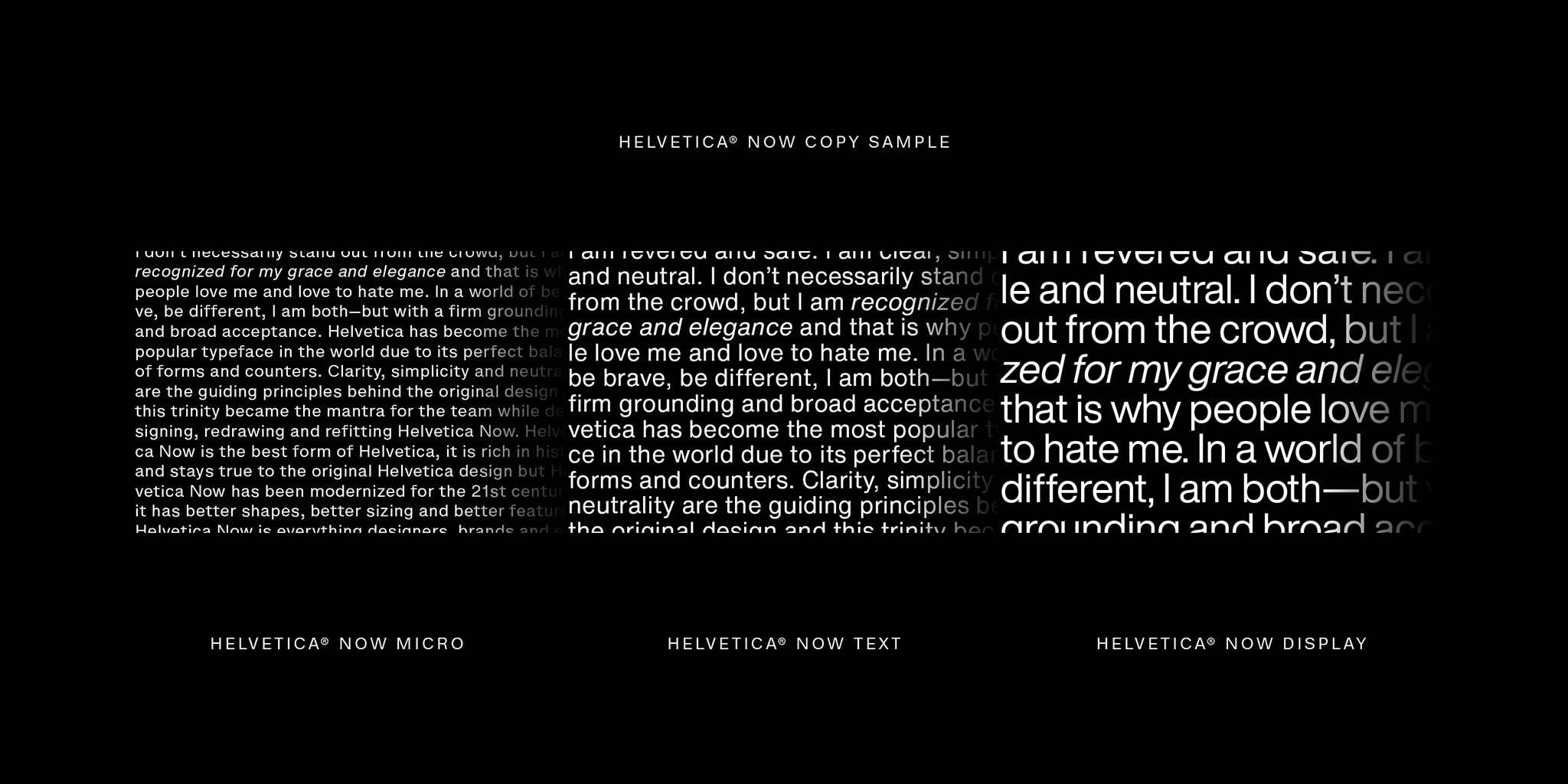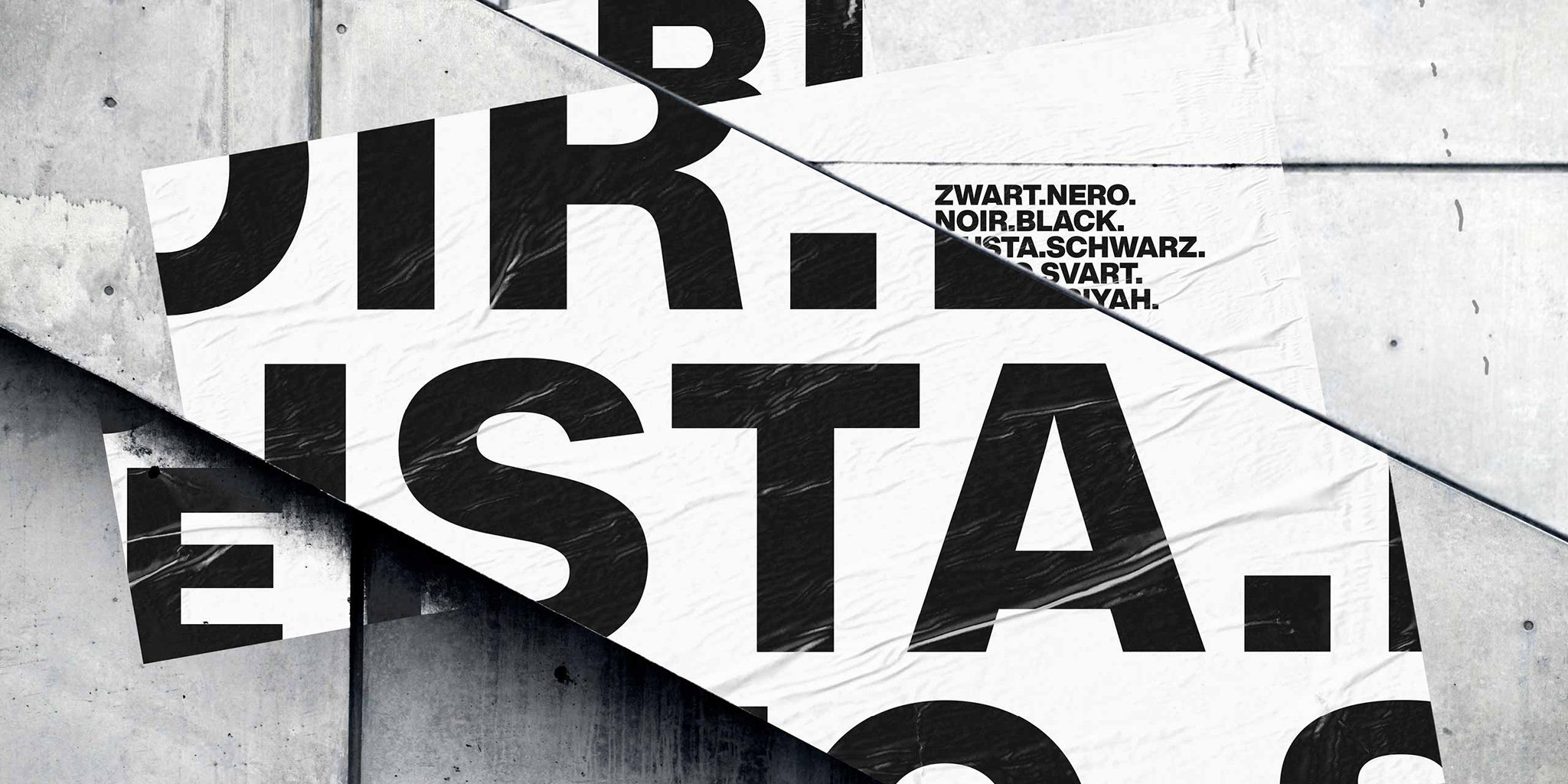
Helvitica đã từ lâu trở thành một trong những bộ font chữ được sử dụng nhiều nhất và nổi tiếng nhất trên thế giới.
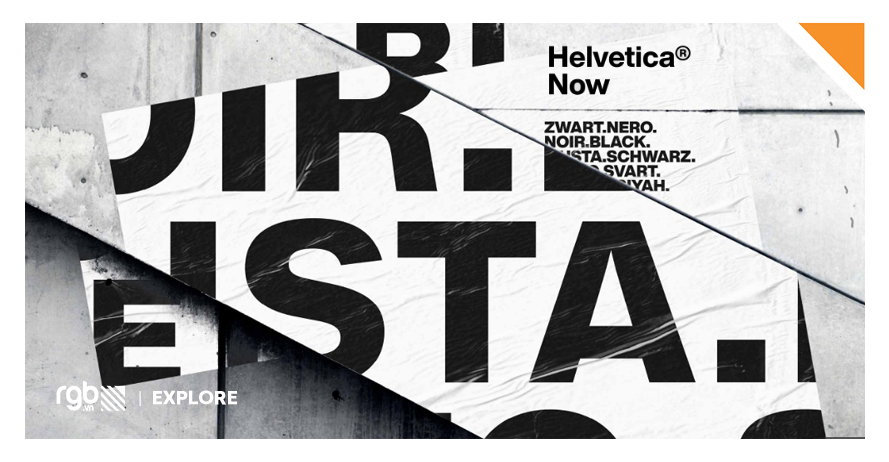
Hiện giờ rất nhiều trang web trên thế giới đang dùng bộ font chữ này. Helvetica là bộ chữ chính thức trong hệ thống tàu điện ngầm ở thành phố New York. Bản thân việc được sử dụng quá rộng rãi của Helvetica đã khiến cho Monotype, công ty “sản xuất” font chữ đang nắm bản quyền sử dụng Helvetica mới đây đã có vài thay đổi trong từng con chữ để khiến nó phù hợp hơn trong thế kỷ XXI.
Bộ font mới này có tên là Helvetica Now. Monotype đã phải bỏ ra rất nhiều thời gian để “vẽ” lại từng ký tự trong số 40 nghìn ký tự của bộ font Helvetica, giúp nó dễ đọc hơn khi có kích cỡ nhỏ trên bao bì sản phẩm hay trên màn hình điện thoại, cũng như khiến nó bớt nhàm chán. The Verge đã có cuộc phỏng vấn Charles Nix, giám đốc mảng font chữ tại Monotype để hiểu thêm về quá trình cập nhật này.
Helvetica Now là gì? Khác biệt của nó với Helvetica và Helvetica Neue là gì?
Bốn năm trước, văn phòng tại Đức của chúng tôi bắt đầu nảy ra ý tưởng tạo ra một phiên bản mới của Helvetica. Họ liệt kê ra vài thứ giúp bộ font này trở nên tốt hơn. Chúng tôi phải nhìn lại quá trình hình thành bộ font này hồi năm 1957. Khi ấy thời đại kỹ thuật số chưa đến, và những chữ cái được “cắt” đúng nghĩa đen theo đúng kích cỡ. Rồi kỷ nguyên số đến, và những sắc thái riêng của những con chữ được cắt ghép kiểu analog chẳng còn nữa.
Trong quá trình 30 năm sau đó, những phiên bản ký tự khác được tạo ra như chữ ‘R’ có chân thẳng, chữ ‘a’ viết như chữ viết tay bị loại bỏ khi kỷ nguyên máy tính cập bến. Vì thế chúng tôi muốn tạo ra những biến thể như vậy và biến chúng trở nên hợp thời hơn. Chữ R in hoa và chữ a thường trên đây chẳng hạn, hoặc chữ u không có ‘đuôi chân serif’ ở cuối ký tự, chữ ‘t’ dọc thẳng đứng, không có nét uốn sang phải, vài dấu câu tròn trịa nữa. Tất cả những điều đó hiện diện để tạo ra cảm giác đã biến mất của bộ font Helvetica cho người đọc.
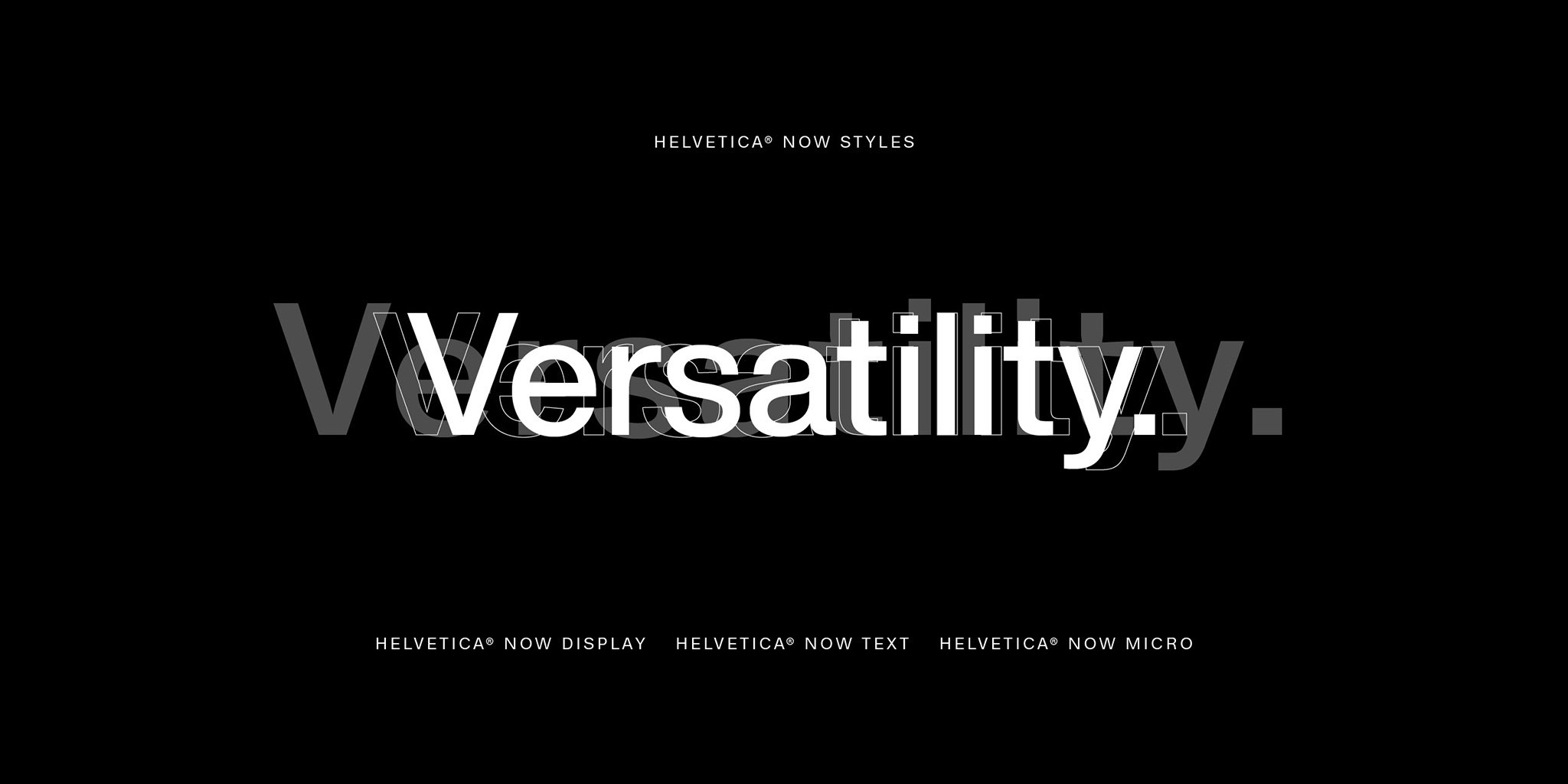
Tôi muốn nói rõ, Helvetica là một bộ font tuyệt vời. Nó dễ đọc, hoàn hảo trong gần như mọi nhu cầu, nhưng Helvetica Now được tạo ra để trở thành một phiên bản tốt hơn thông qua việc giới thiệu lại những thứ chúng tôi đã từng làm trong quá khứ, cùng với đó là cập nhật bộ font dựa trên nhu cầu sử dụng của con người.
Chúng tôi đưa ra những thay đổi theo thứ tự, từ góc nhìn của khách hàng, của người dùng, rồi đến góc nhìn của những người thiết kế. Thay đổi bộ font chữ nghĩa là khả năng phóng to thu nhỏ từng con chữ cũng sẽ thay đổi. Điều này khiến chúng tôi tính toán nhiều nhất. Lý do là mỗi khi nhắc về một bộ font Helvetica mới, thường tôi sẽ nhún vai: “Có cần thiết phải tạo ra một bộ font Helvetica mới không?” Nhưng rồi bạn nhìn thấy nó, và nhờ khả năng thay đổi kích cỡ tùy ý, nó giống như gặp lại một người bạn cũ vậy. Tuyệt lắm.
Nếu Helvetica đã trở thành tiêu chuẩn như vậy, thì làm thế nào để tạo ra một phiên bản mới của nó?
Làm thế nào để thiết kế lại bộ font chữ nổi tiếng nhất lịch sử ấy hả? Thì vừa làm vừa lo thôi. Làm hỏng cái này thì coi như bung bét hết cả. Dĩ nhiên là chúng tôi sẽ không làm hỏng bộ font cả thế giới yêu thích đâu, nhưng đi kèm với đó là rất nhiều việc phải làm: Tua ngược về quá khứ, tìm hiểu lịch sử bộ font, xem tất cả những phiên bản Helvetica từ năm 1957 đến giờ, hiểu cách nó thay đổi và những bước nào sai, để tránh những lỗi không đáng có và tìm ra những chi tiết cần được bảo tồn nguyên vẹn.
Làm việc này cũng giống như hành nghề y với lời thề Hippocrate ấy: “Không được làm điều gây hại”. Bất kỳ con chữ nào được thiết kế lại cũng cần áp dụng ba nguyên lý, đơn giản, rõ ràng và trung lập. Phần việc của tôi khi tạo ra Helvetica Now là thiết kế lại những con chữ nhỏ cỡ 6, 5, 4, hoặc thậm chí chỉ nhỏ bằng vài pixel trên màn hình điện thoại của các bạn.
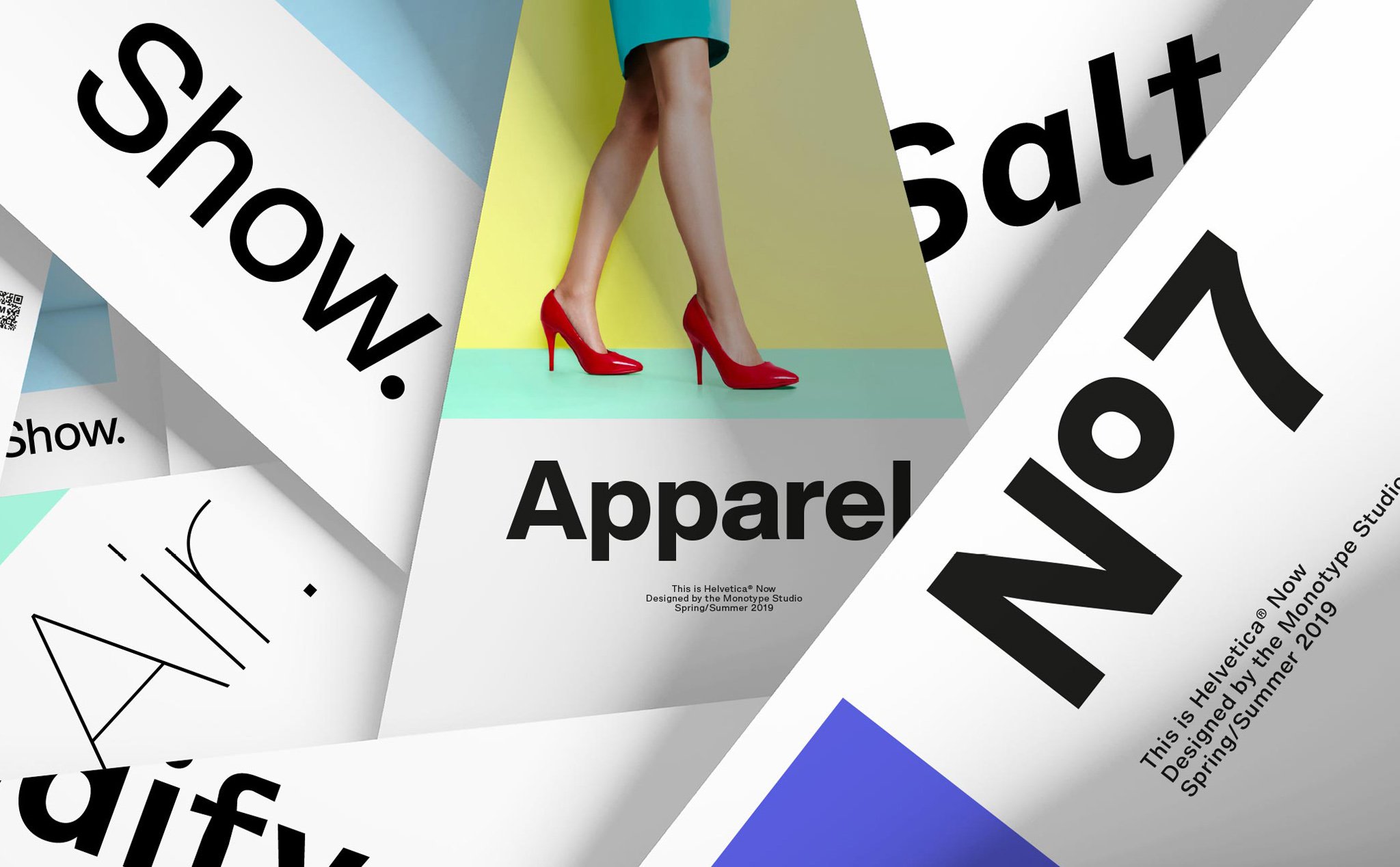
Làm vui lắm, tôi được xem những bản in kim loại cỡ 6pt thời 1957-1960 của Helvetica ở Đức và Thụy Sỹ, và nghiên cứu khoảng cách giữa những con chữ. Sau khi sắp xếp những chữ cái hợp lý, tôi lại xáo tung chúng lên để nhận ra những khác biệt. Chỉ có thể nhận ra những khác biệt khi bạn thay đổi trình tự những chữ cái thôi. Nếu bạn nhìn chữ ‘F’ viết hoa, hoặc chữ ‘t’ thường, ý nghĩ đầu tiên luôn là “có cách nào khiến chữ cái kích thước 3pt, hiển thị trên màn hình Retina hay trên bản in độ nét cao rõ ràng hơn không?”
Có những khoảnh khắc trong cuộc sống khi bạn bất ngờ hiểu được thế nào là niềm vui. Tôi không muốn nói quá lên, nhưng đó chính là cảm giác của tôi khi tạo ra những ký tự Helvetica Now ở kích thước cực nhỏ. Mọi lý thuyết mà chúng tôi nghĩ ra để làm thế nào cho những ký tự cỡ nhỏ dễ nhìn hơn nhưng cùng lúc giữ lại được bản sắc của Helvetica đều trở nên hoàn hảo.
Trước kia Helvetica đến cỡ 6pt là chẳng còn đường nét nào nổi bật nữa, vì kích thước chữ và khoảng cách giữa những ký tự trở nên rất nhỏ. Nhưng khi nhìn thấy Helvetica Now ở kích thước 3pt, tôi mới thật sự cảm thấy sung sướng.
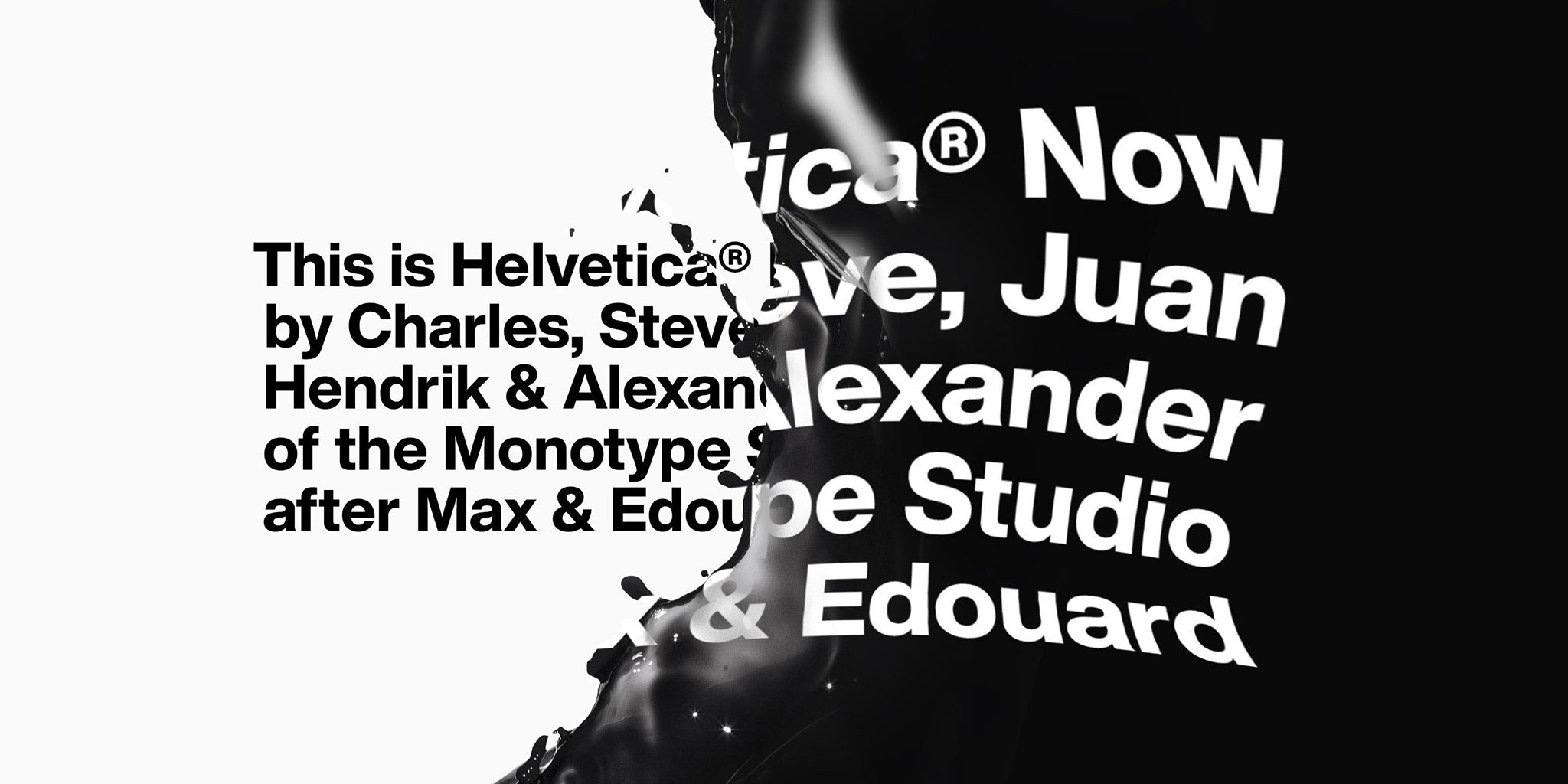
Vậy có ký tự nào khiến anh cảm thấy tự hào nhất khi tạo ra không?
Có, ký hiệu của đồng Bảng Anh (£). Trước đó tôi đi xem 1 trận bóng chày với một người bạn cũng là một nhà thiết kế, anh này chia sẻ rằng một người bạn khác từng nói với anh ấy rằng mỹ thuật là quá trình tạo ra một thứ có giá trị tuyệt hơn so với những gì đáng lẽ ra nó phải sở hữu. Và thế là tôi bỏ ra một khoảng thời gian dài hơn bình thường chỉ để chỉnh ký hiệu £ sao cho ở kích thước 3pt nó vẫn rõ ràng dễ nhìn. Nó giống như một bức họa theo trường phái ấn tượng ấy.
Tôi luôn chia thế giới typography ra làm hai dạng, chữ lớn trong dòng title (display typeface), và chữ nhỏ trong các đoạn văn (text typeface). Những con chữ lớn chính là những thứ khổng lồ gây lôi cuốn con người. Chúng ta bị cuốn hút bởi những con chữ trên những dòng title, những câu slogan quảng cáo, nhưng kỳ thực những ký tự trong các đoạn văn xuất hiện nhiều hơn một cách rõ ràng. Tôi nghĩ rằng Helvetica Now Condensed hay Expanded sẽ trở thành những công cụ giúp ích hữu hiệu cho những nhà thiết kế.